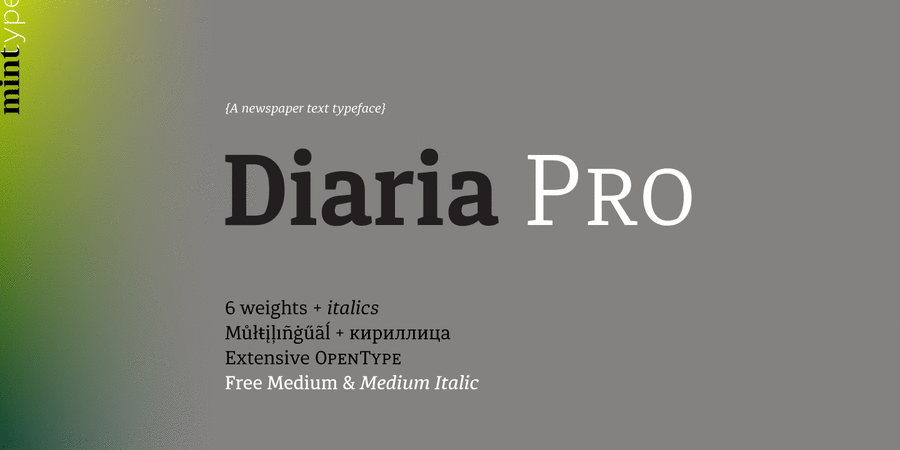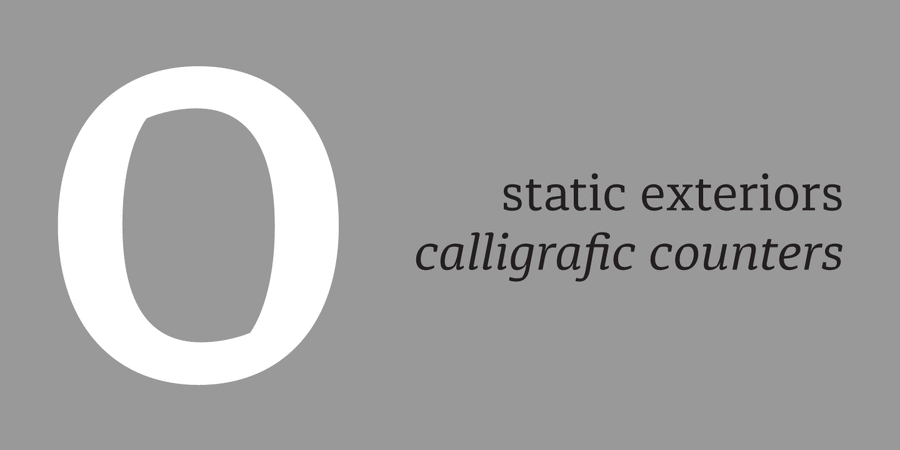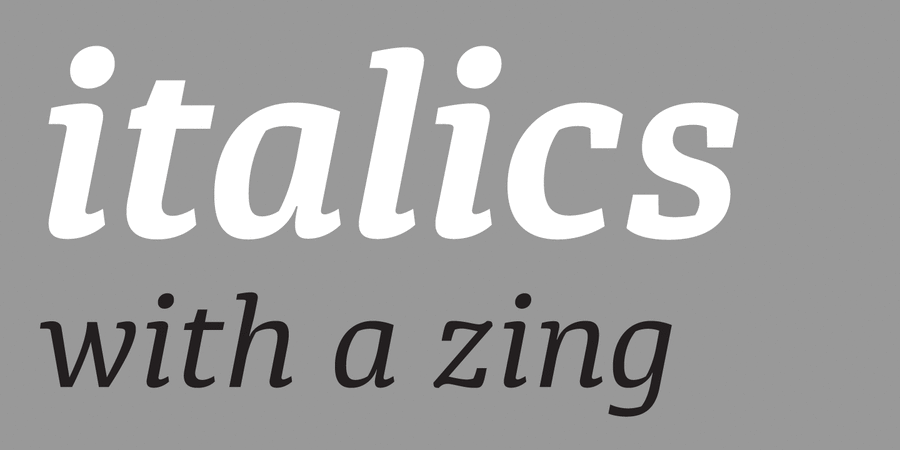
Розробка гарнітури Diaria почалася в якості курсової роботи з предмету «Архітектура шрифту» магістерської програми «Просунута типографіка» в EINA, університетському центрі дизайну і мистецтв Барселони, під керівництвом Лаури Мазаґер та Іньїґо Хереса Кінтани. Згодом він перетворився на Diaria Pro – розвинену шрифтову гарнітуру з кирилицею, капітеллю та різними OpenType-фичами.
Diaria Pro – це слабоконтрастний шрифт із зарубками, розроблений для текстового застосування у газетах. Його великі рядкові символи й статичні зовнішні контури сприяють комфортному читанню вузьких колонок, а каліграфічні внутрішні просвіти, динамічні зарубки та гуманістичні деталі, як нахил осі напливу, створюють неповторний характер.
Крім розширеної мовної підтримки, Diaria Pro включає багато OpenType-фич: класичні та вибіркові лігатури, капітель, 6 наборів цифр, верхні й нижні індекси, дроби, маюскульна пунктуація і деякі мовні альтернативи.
У Diaria Pro є також компаньон без зарубок – Diaria Sans Pro. Шрифт розробив і випустив Андрій Константинов у студії Mint Type в 2015 році.
Асоціації з сімейством шрифтів Diaria ProОсобистість і характер гарнітури:
делікатний, спокійний, рівний, гармонійний, універсальний, зрозумілий, Простий, нейтральний, середній, звичайний, діловий, врівноважений, космополітичний, ненав'язливий, помірний, технічний, сучасний, точний, логічний, непомітний, практичний, оптимальний, доступний, статичний, культурний, освічений, стійкий, формальний, серйозний, твердий, якісний, ввічливий, гладенький, пластичний, переконливий, суворий, мотивуючий, відповідальний, модний, стабільний, надійний, впевнений, сильний, індустріальний, техногенний, авторитетний, значний, гучний, амбітний
Місто, освіта, наука, суспільство, література, фінанси, вчитель, ліки, юрист, адвокат, правосуддя, економіка, медицина, банк, суд, влада, політика, гроші, новини, аптека, архітектура, конструктор, техніка, прилад, промисловість, інструмент, механіка, ремонт, дизайн, охорона, захист, поліція, будівництво, взуття, технології Гарнітура має ознаки стилів: